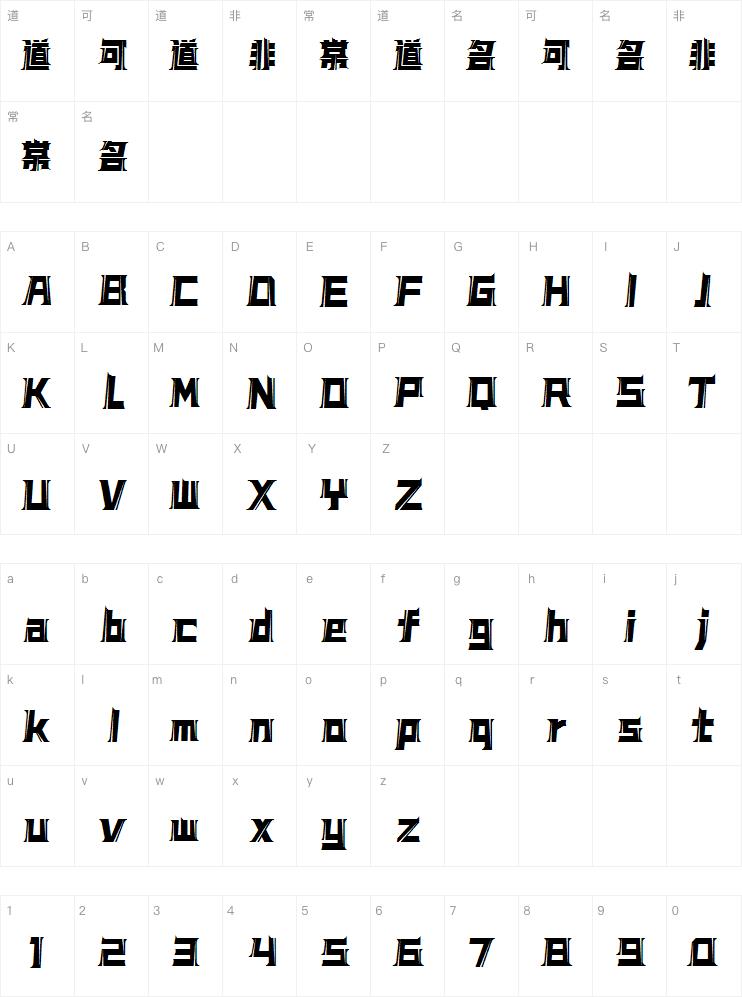
潮笑社核冲击波简 超黑是一款充满力量与攻击感的创意黑体。整体字形饱满,左侧轮廓如梯形倾斜塑造高挺仰视的高重心感,笔画设计硬朗直挺,粗壮有力,笔画的切口与转折处有尖角装饰,整体具有高昂,强势与锋锐的特点贯穿主笔的裂隙高光设计制造独特动态视觉效果,能适用于游戏场景、商业广告、包装印刷及品牌宣传等场景的使用需要。